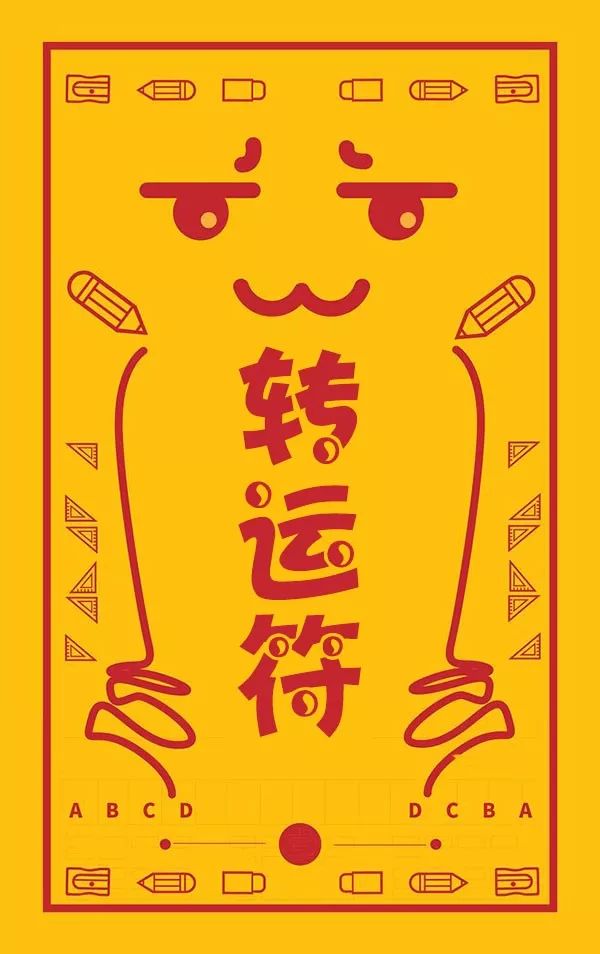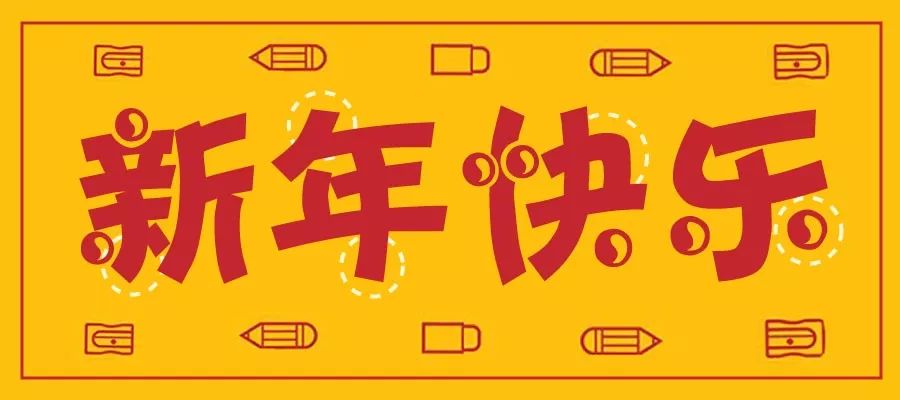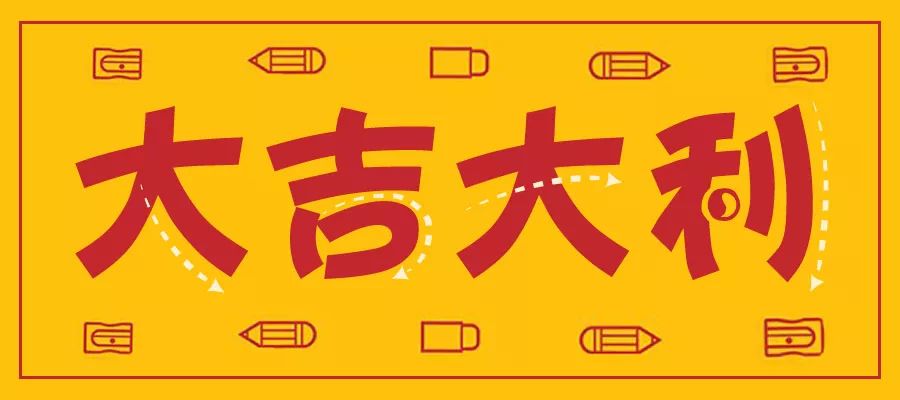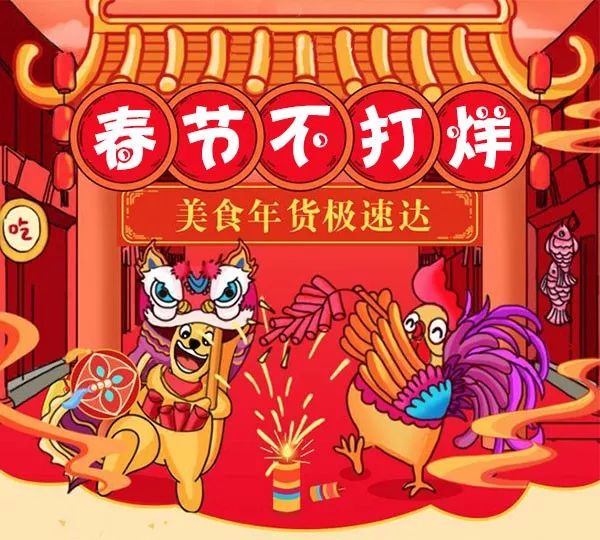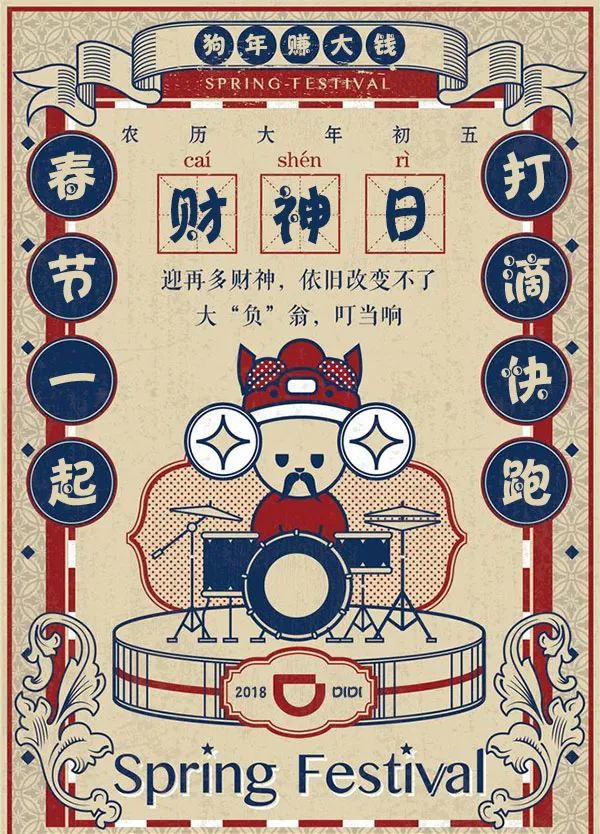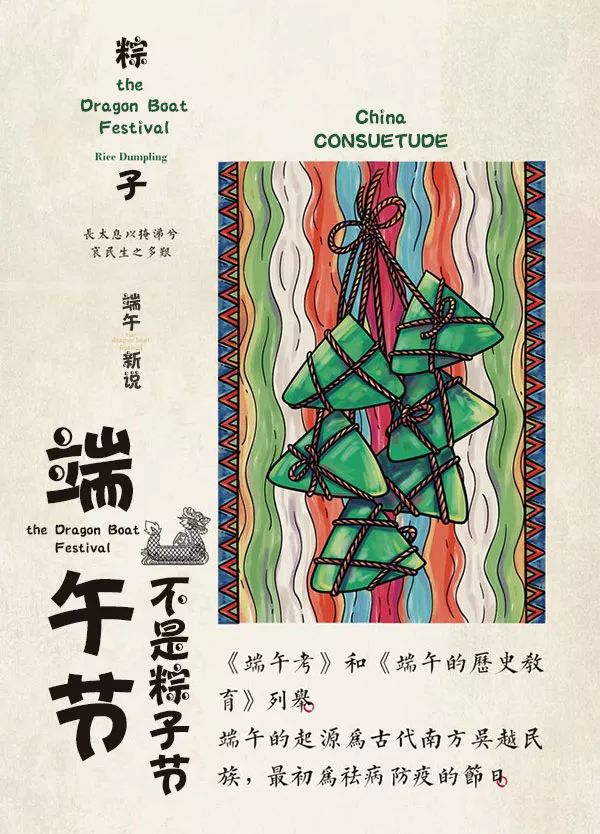
汉仪太极体介绍,汉仪太极体使用案例分享
开年巨献转运神器--汉仪太极体
有了这款字保你2018好运到!
字体将阴阳之道完美融合
以太极图为核心化无形之气为有型之字
灵动的笔画起伏间使阴阳二气自然消长
平稳的视觉重心更是让字体行气流转不息
有了这款字悄然间就可改变你一方风水格局
让你在今年鸿运当头
如若遇见迷信风水的甲方爸爸
更是你克敌制胜的不二之选
小编最后再送你几套“转运图”
你随身佩戴于胸前保你方案一次过稿